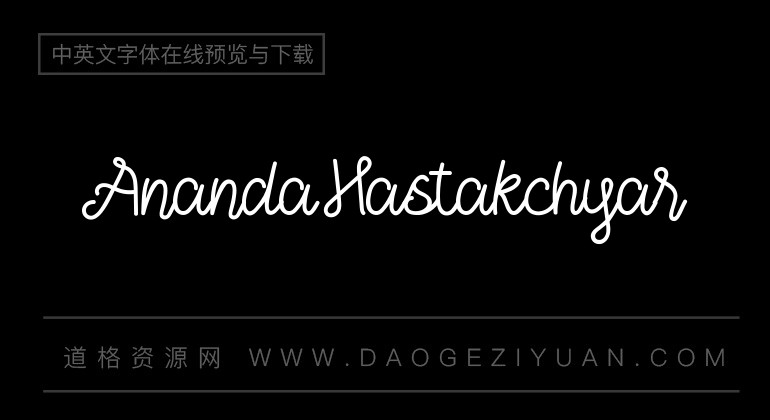
Ananda Hastakchyar
Ananda Hastakchyar 字体是一款新型的字体,它使用了一种独特的设计,可以提供清晰、鲜明、简洁的文字表现。它采用细节精致的笔触,使文字表现更加清晰,并且可以更好地表达文字的意义。Ananda Hastakchyar字体可以更好地提升文字的美感,给读者更好的阅读体验。
Ananda Hastakchyar是一款非常不错的手写艺术字体,具有很好的视觉感,适合于文化类的宣传设计、商业类品牌的广告和产品包装设计以及个性化文字排版等较多场景。